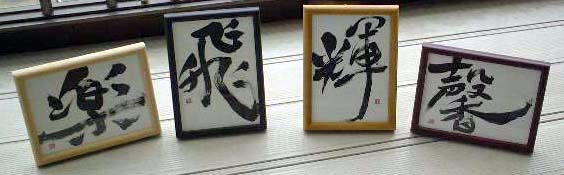
【書 「楽」「飛」「輝」「馨」】 紙の大きさ:キャビネサイズ 仕上げ:マットなし額装(木地色、黒、チーク色、マホガニー色フレーム) (愛知県:(株)ウメオカ様) |
海外のお得意様へのおみやげとして依頼を頂きました。漢字として読める”いかにも書”というのをテーマに、よい意味の言葉を選びました。ウメオカの社長さんとスタッフの大池さんより、渡す人へのそれぞれの気持ちとプロフィールを伺って書いた作品たちです。文字屋の書が初めて渡米! カンゲキ! <ヨロコビの声> |